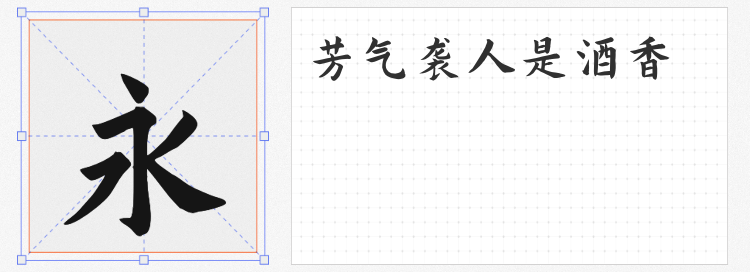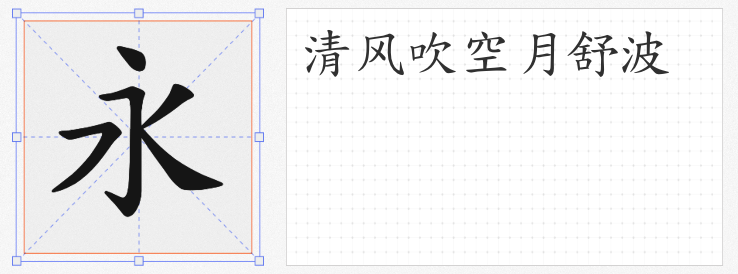
免费商用标题字体精选:四款兼具设计感与实用性的开源佳作
在商业设计中,标题字体的选择直接影响视觉传达的冲击力与专业度。本文精选四款免费可商用的开源字体,它们以独特的设计语言与广泛的适用性,成为标题设计的理想之选。
1. 寒蝉书体·春秋 秋鸿
基于开源字体演示秋鸿楷拓展字形,寒蝉书体·春秋 秋鸿以传统书法为基底,融入现代设计语言。其笔画粗细对比强烈,横竖转折处保留毛笔书写的自然飞白,赋予标题古朴而灵动的气质。适用于文化、艺术类海报标题,尤其适合需要传递历史厚重感或东方美学的场景。
2. 寒蝉正楷体
作为全字库正楷体与西文字体Gentium的整合优化项目,寒蝉正楷体以清晰端正的楷书风格著称。其笔画横平竖直,转角处理利落,中宫紧凑而字间距宽松,确保标题在小字号下仍保持高可读性。同时,西文字符与中文风格高度统一,适合学术报告、商务文档等需要权威感与国际化的标题设计。
3. 霞鹜文楷 GB Light
衍生自日本Klee One字体,霞鹜文楷 GB Light融合仿宋的秀丽与楷体的端庄,形成兼具古典韵味与现代感的独特风格。其笔画纤细而不失力度,字面略宽,排版时呈现呼吸感与节奏感。Light字重尤其适合女性向、文艺类标题,如时尚杂志封面、手账设计等,温润的视觉体验能有效提升受众好感度。
4. 寒蝉活仿宋Regular
以朱雀仿宋与西文字体Simonetta为蓝本,寒蝉活仿宋Regular通过斑驳纹理与手写质感还原活字印刷的复古韵味。其字形略带倾斜,笔画边缘保留轻微毛边,营造岁月沉淀的沧桑感。适配英文与标点符号的设计,使其成为复古风海报、音乐专辑封面的标题首选,尤其适合需要故事感与艺术张力的视觉表达。